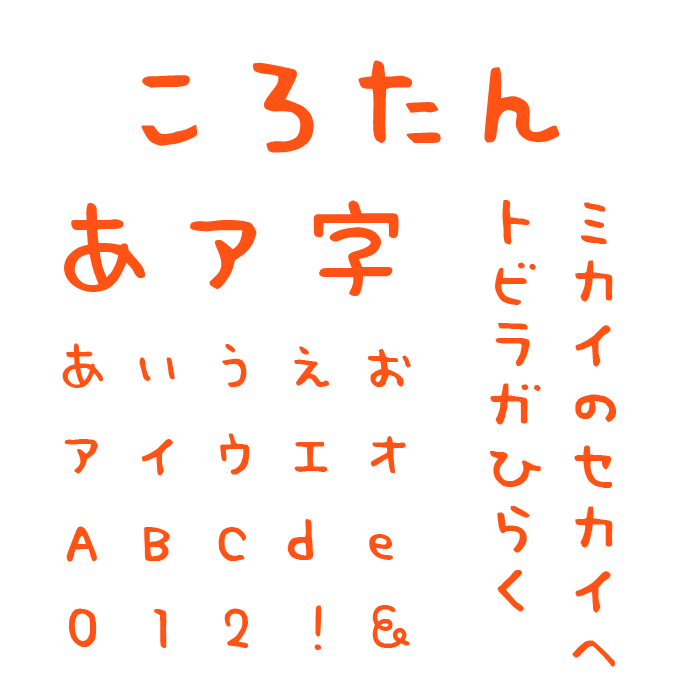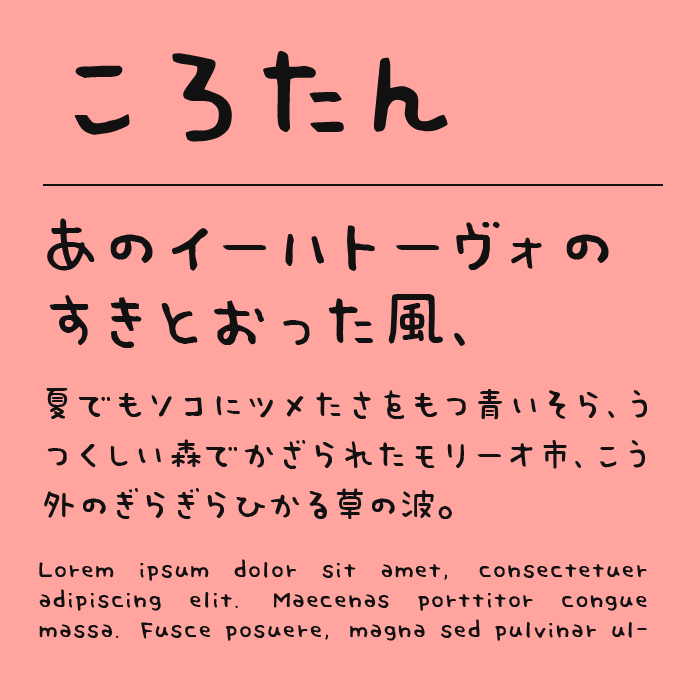
ころたんフォントは、ぽてっと丸いシルエットが特徴の、おっとりした印象の手書きフォントです。文字の輪郭が太めに整えられており、安定感と安心感がある見た目です。ひらがなの曲線がとくに愛らしく、親しみやすさが感じられるフォントです。
子ども向けのコンテンツや、ポップな広告・パッケージデザインによく合います。まるで「ころん」としたキャラクターが喋っているような、表情豊かで楽しい雰囲気が伝わってきます。親しみやすさと可愛らしさを両立したフォントです。
収録文字は、漢字・ひらがな・カタカナ・アルファベット・数字・記号が収録。